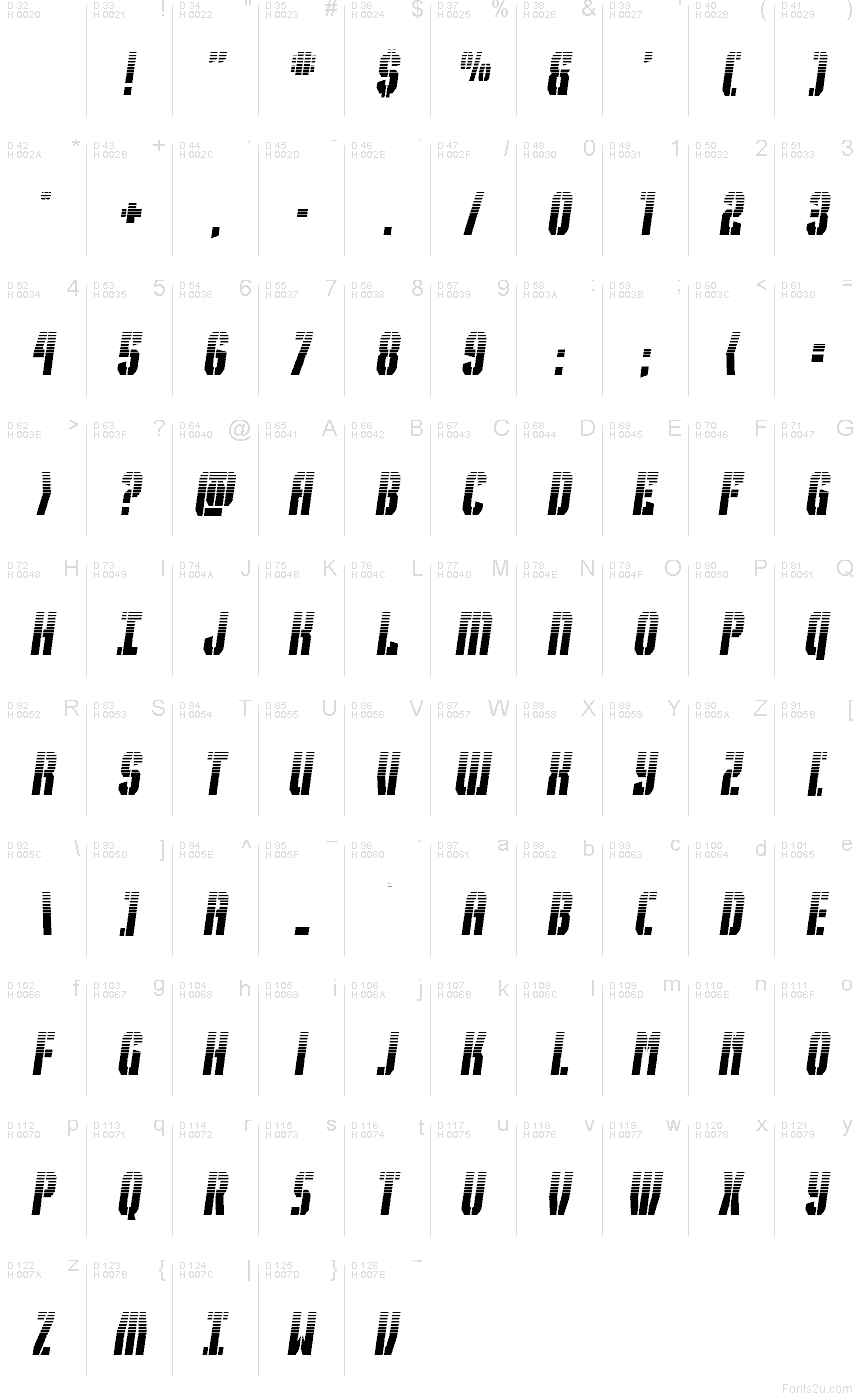
Gorilla Warfare Halftone SemIt de Iconian Fonts es una tipografía display gratuita de estilo militar con una actitud contundente, ideal para carteles. Sus mayúsculas mezclan una estructura sólida, similar a la de las plantillas, con un fino rayado horizontal de medios tonos en la parte superior; esto hace que las letras parezcan desgastadas por la batalla, casi como si hubieran sido impresas mecánicamente, con cortes diagonales afilados que mantienen un ritmo agresivo y compacto.
Esta fuente gratuita encaja a la perfección en logotipos de videojuegos, títulos de películas de acción, diseños de ropa urbana (streetwear), carteles de eventos y titulares que necesiten un toque táctico y rudo, sin caer en el típico cliché del camuflaje. También funciona de maravilla en titulares cortos y monogramas, ya que las rayas quebradas y las formas de bordes duros dan a unas pocas letras el impacto suficiente para sostener todo el diseño.
Gorilla Warfare Halftone SemIt
Daniel Zadorozny